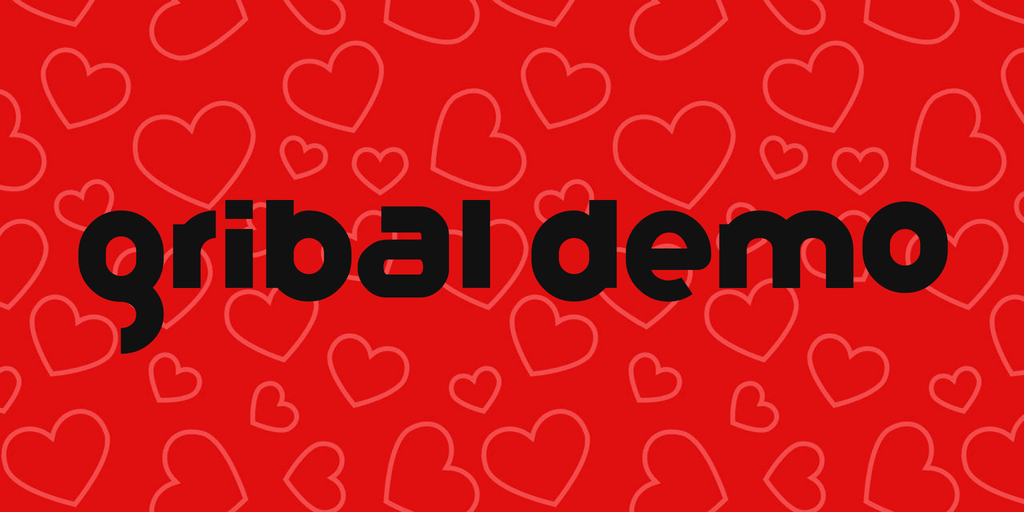
Gribal Demo Font Family – Fonte Grátis
Gribal Demo Font Family
A Gribal Demo Font Family é uma elegante família de fontes sans-serif criada pelo designer Hamilton para quem está procurando aperfeiçoar seu trabalho com tipografia, sem comprometer a qualidade ou a funcionalidade. Esta demo version oferece uma visão inspiradora da riqueza e variedade desta família de fontes, permitindo um primeiro contato rico em detalhes e harmonia. Embora este seja um versão limitada, ela destaca os principais elementos do design gráfico, incluindo linhas leves, curvas agradáveis ao olho, e espaçamento equilibrado. A Gribal Demo permite que designers de nível intermediário ou avançado experimentem as potencialidades desta família antes de investir em uma versão completa, oferecendo um excelente ponto de partida para qualquer projeto gráfico. Para os profissionais que buscam incorporar esta fonte em seus projetos comerciais, a equipe do StudioTypo disponibiliza um link onde você pode obter autorização e acesso a versões completas da fonte. Estamos aqui para fornecer suporte ao ajudá-lo a integrar perfeitamente esta família de fontes na sua próxima criação gráfica. Junte-se a nós nesta jornada de descoberta gráfica, onde cada letra é uma história, e a Gribal Demo Font Family pode ser o instrumento perfeito para contar suas próprias.